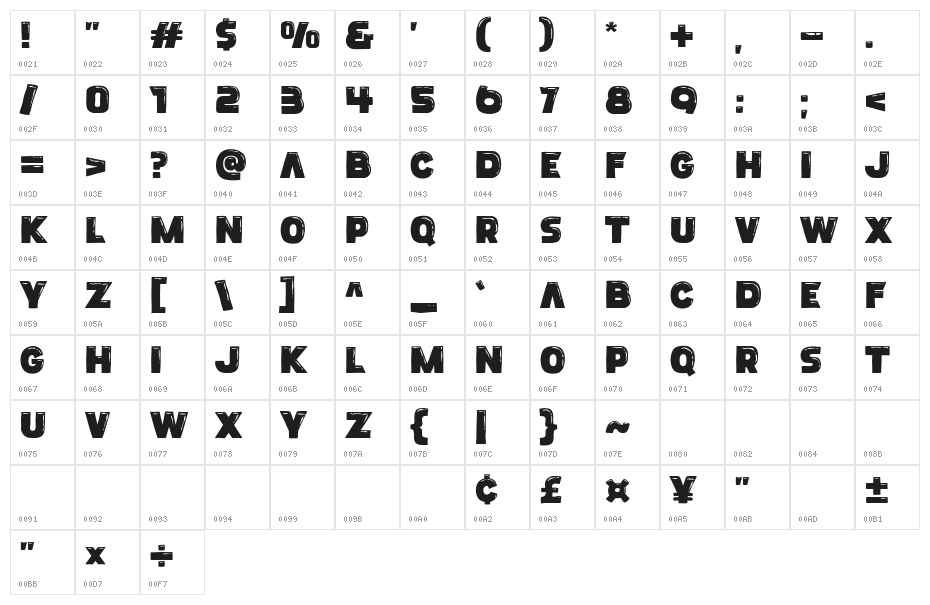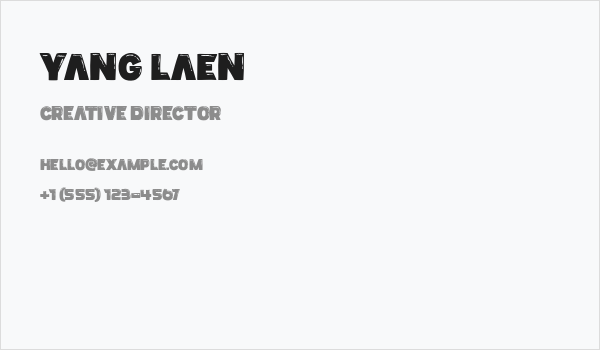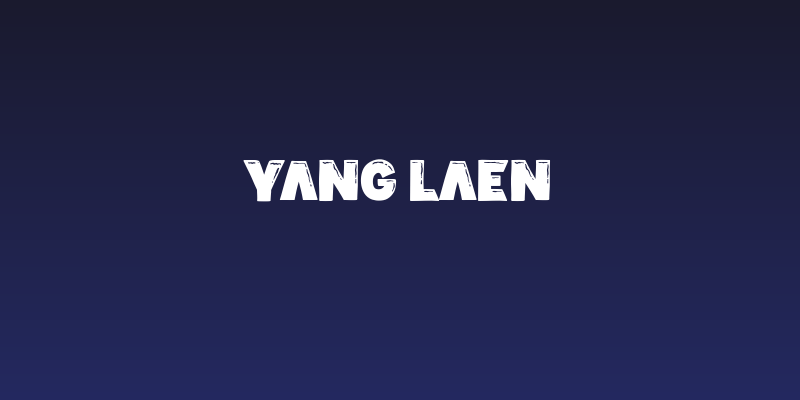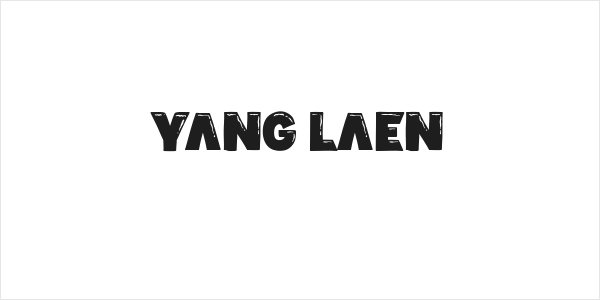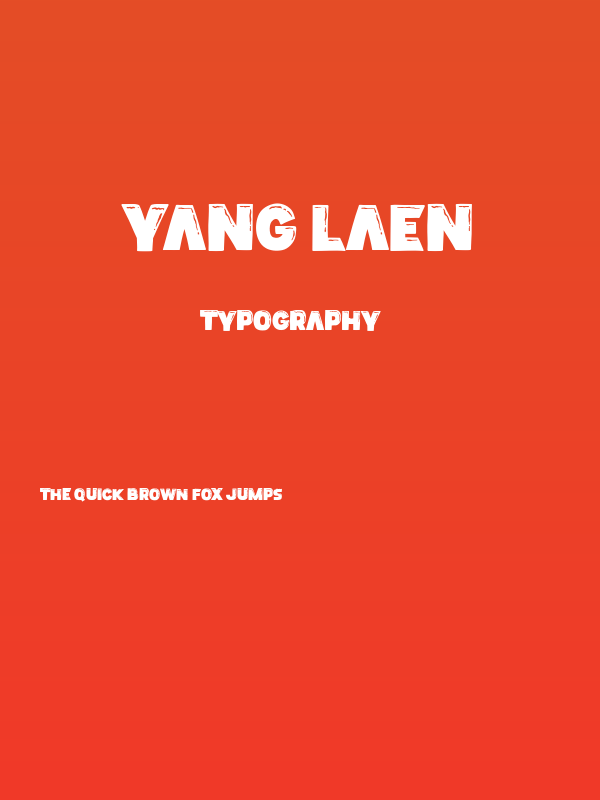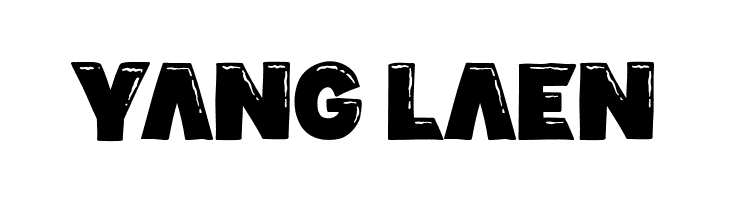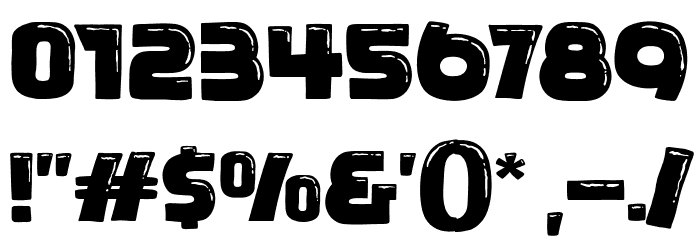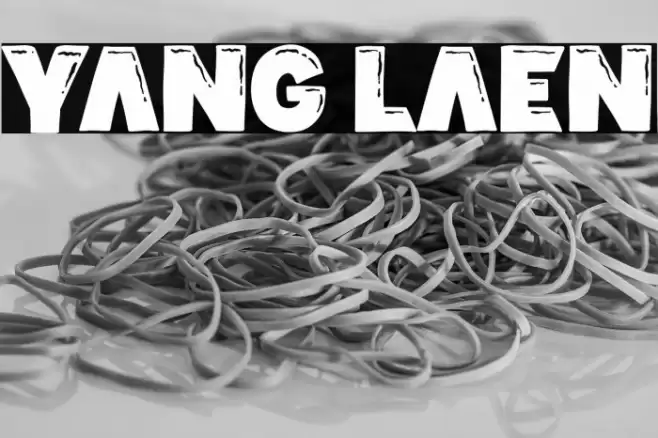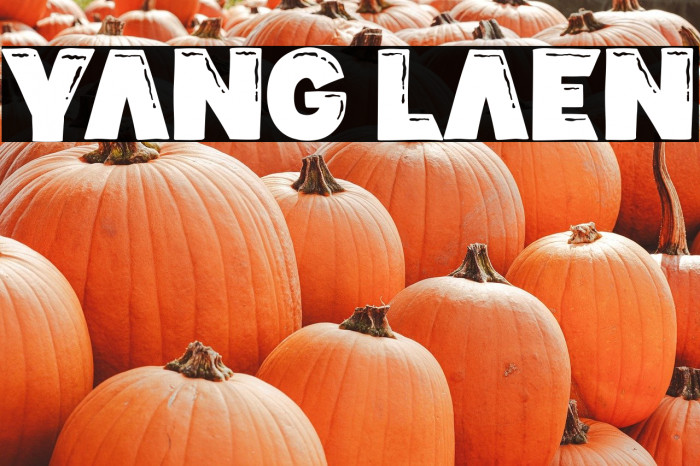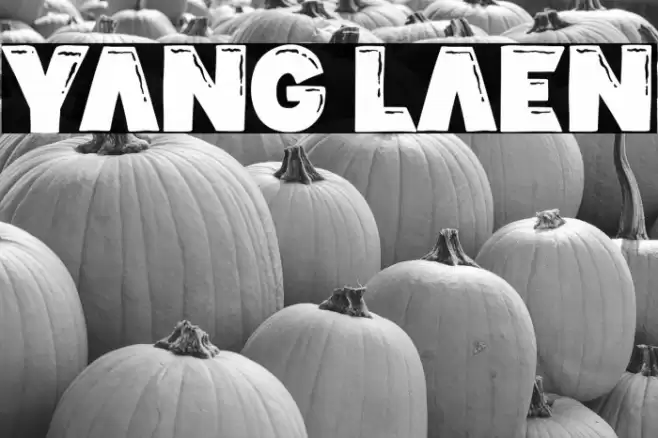
Yang Laen Font
| समग्र शैली | Vintage |
| उपयोग का मामला | Logos, Posters, Branding |
| सुझाए गए प्रोजेक्ट | Ideal for projects that require a vintage or rustic look, such as posters, logos, branding for outdoor or adventure-themed products, and apparel design. |